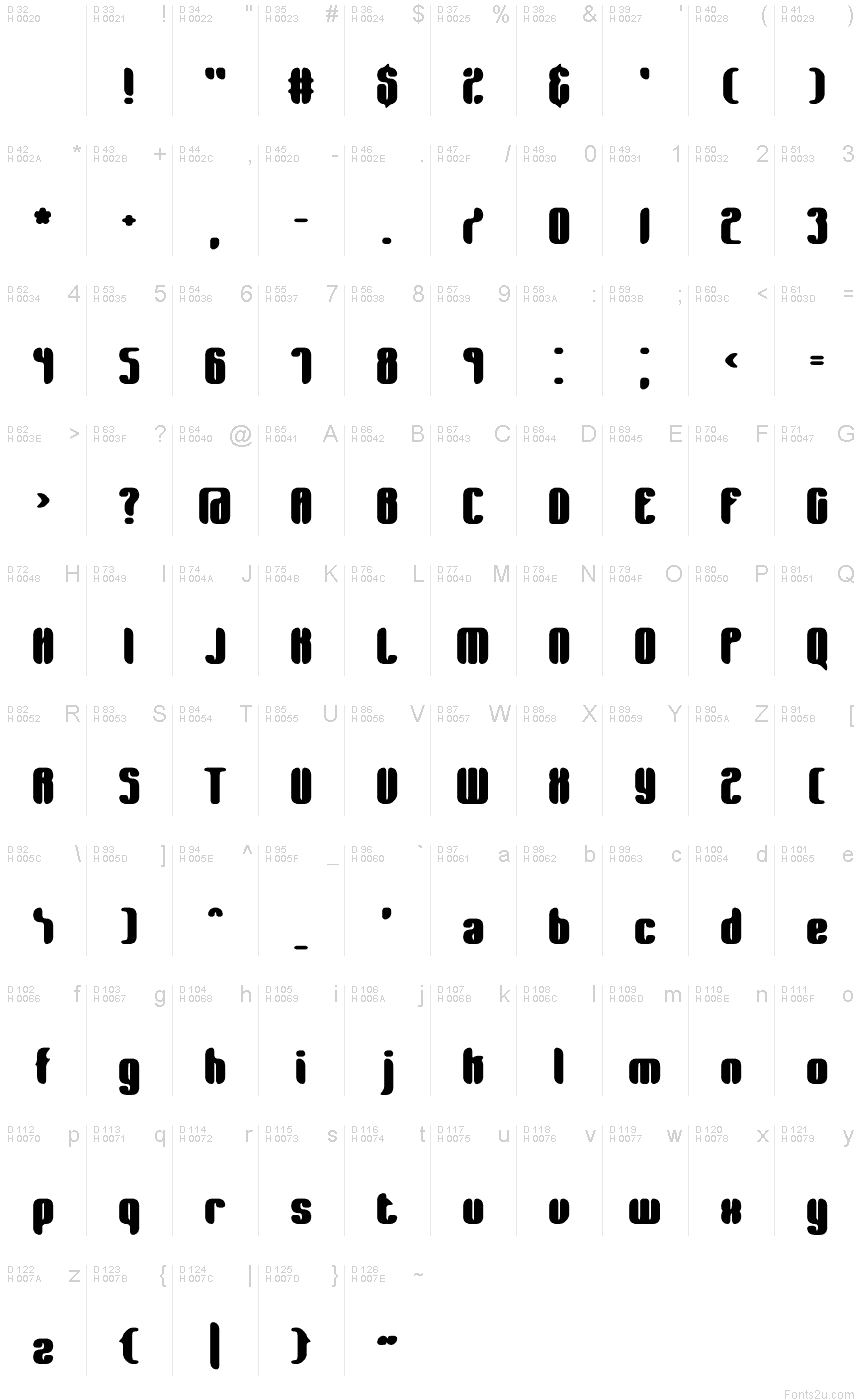
Wager Won BRK
Wager Won BRK od ÆNIGMA Fonts to darmowy krój displayowy inspirowany latami 70., z wyrazistym, obłym charakterem. Litery sprawiają wrażenie miękkich i napuchniętych, z głębokimi krzywiznami, łagodnymi łączeniami i lekką nutą zabawy, która sprawia, że ciężkie kształty nie wydają się sztywne.
Świetnie sprawdzi się na plakatach, okładkach albumów, w identyfikacji wizualnej kawiarni, na opakowaniach i w krótkich nagłówkach, wszędzie tam, gdzie liczy się ciepły, retro klimat. Jako darmowy font, nadaje się również do plansz tytułowych, okładek i szkiców logo, ponieważ te szerokie, pękate formy prezentują się najlepiej, gdy słowa są krótkie, a przekaz wyrazisty.